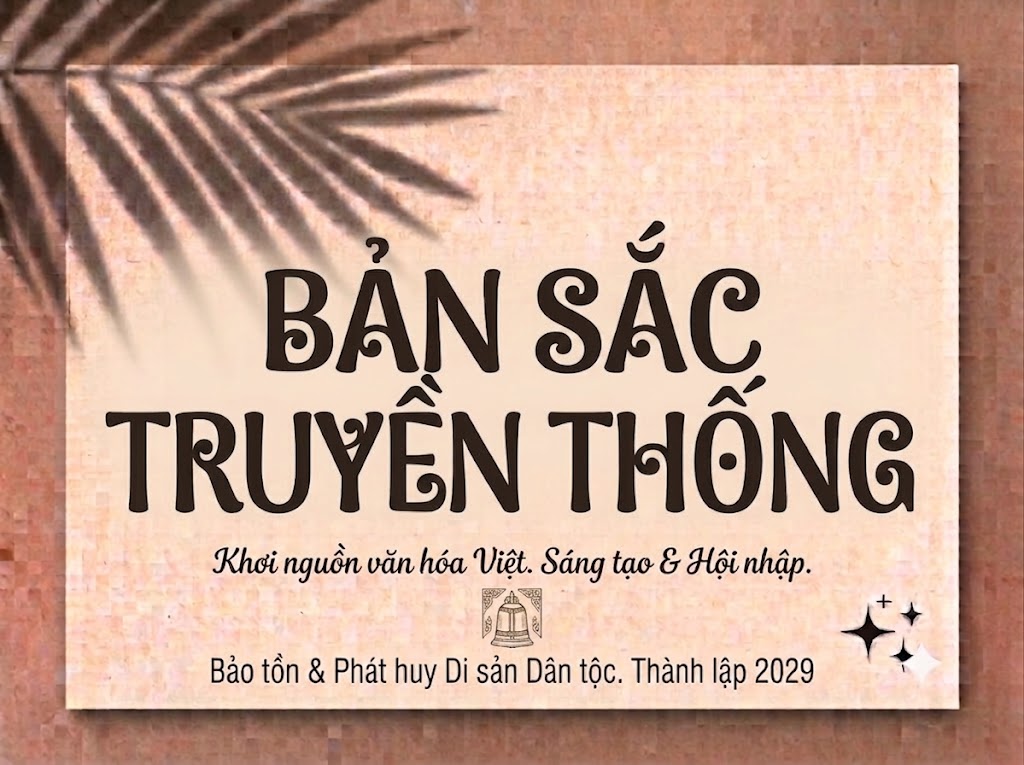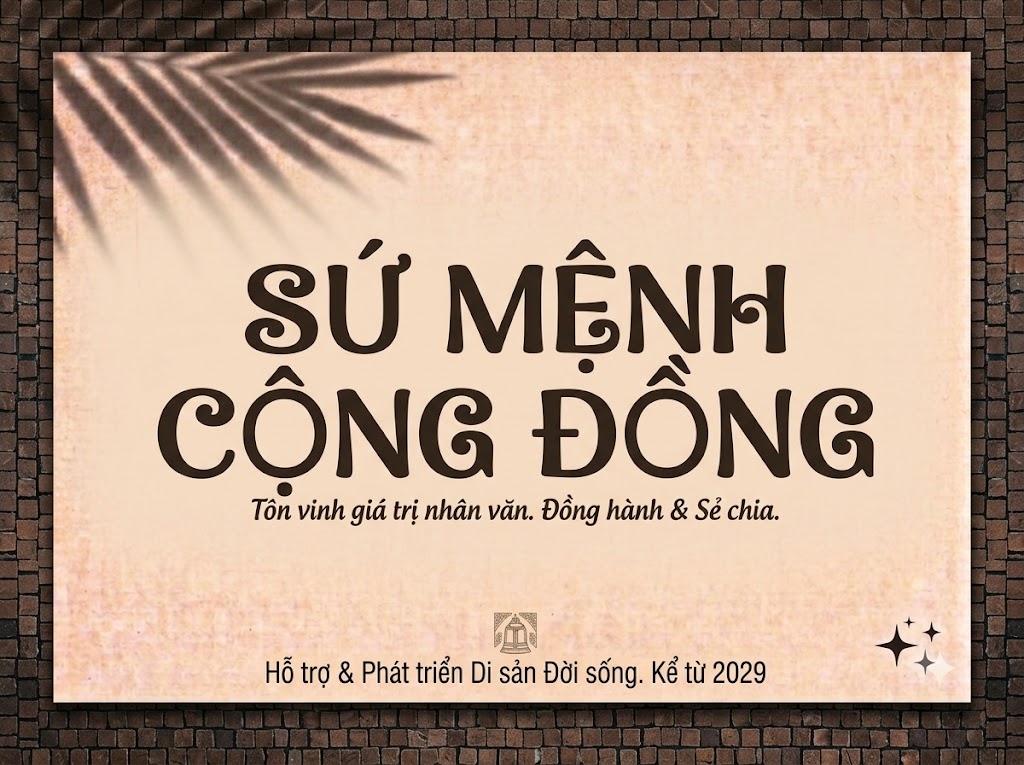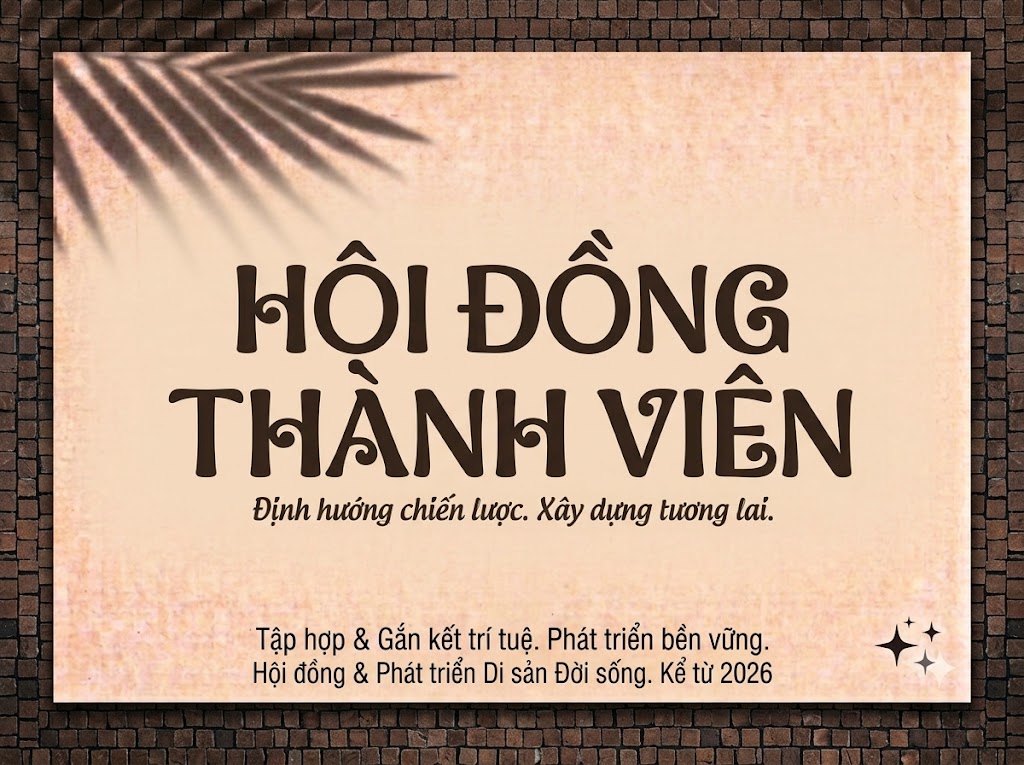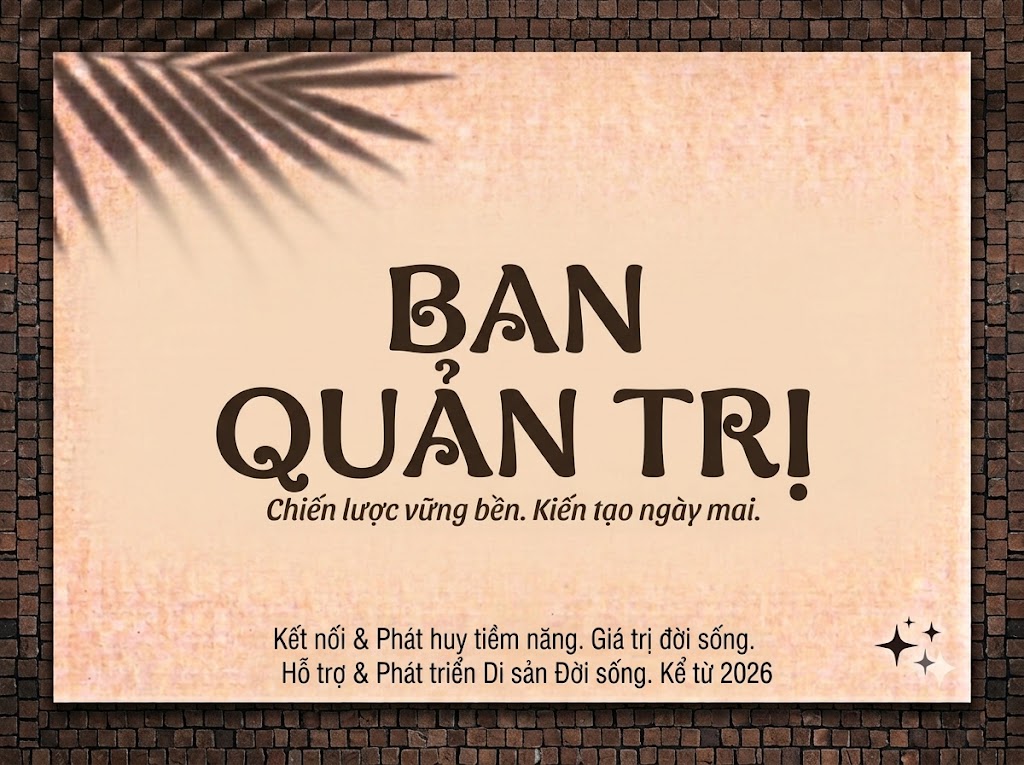
1FTV VIP Boruna
Trong xu hướng thiết kế đồ họa đương đại, ranh giới giữa chữ viết (typography) và hội họa ngày càng trở nên mờ nhạt. Một phông chữ tiêu đề xuất sắc giờ đây không chỉ làm nhiệm vụ truyền tải thông tin đơn thuần, mà bản thân nó phải là một tác phẩm nghệ thuật có khả năng tự kể câu chuyện của riêng mình.
Nếu bạn đã quá quen thuộc với các dòng Serif tân cổ điển thẳng thớm, nghiêm nghị và đang tìm kiếm một làn gió mới vừa sang trọng, quý phái lại vừa có nét uốn lượn, bay bổng đầy ma mị, thì 1FTV VIP Boruna chính là câu trả lời hoàn hảo dành cho bạn.
Giới thiệu về font 1FTV VIP Boruna
Font 1FTV VIP Boruna là một bộ chữ hiển thị có chân (serif display) mang phong cách nghệ thuật đương đại, nổi bật với sự kết hợp táo bạo giữa cấu trúc chữ Serif cao cấp và các nét cắt lượn sóng đầy mê hoặc.
Tên phông chữ: 1FTV VIP Boruna.
Đặc điểm thiết kế độc bản của VIP Boruna
Sức hút thị giác đầy mê hoặc của font 1FTV VIP Boruna đến từ sự kết hợp tài tình giữa cấu trúc hình khối hiện đại và vũ điệu “chất lỏng” mềm mại:
Độ tương phản nét cực hạn (High Contrast): Thừa hưởng DNA của dòng Modern Serif cao cấp, phông chữ sở hữu các nét dọc cực kỳ dày dặn, vững chãi đặt cạnh những nét ngang siêu mảnh. Sự tương phản này tạo nên một hiệu ứng thị giác vô cùng kịch tính và sang trọng.
Biến điệu lượn sóng (Liquid/Wave Accents): Điểm đắt giá nhất của VIP Boruna nằm ở cách tạo hình các nét cắt lượn sóng cực kỳ nghệ thuật ở phần bụng và tâm chữ cái. Nhìn vào các ký tự như o, e, a, g, p, bạn sẽ thấy các đường sóng ngang mềm mại phân tách tâm chữ một cách ngẫu hứng. Chi tiết này gợi liên tưởng đến những gợn sóng nước lăn tăn hay xu hướng thiết kế “Y2K liquid” đang rất thịnh hành.
Chân chữ vạt nhọn (Flair Serif) sắc sảo: Phần chân chữ được gọt giũa dứt khoát, gọn gàng, giúp cân bằng lại sự mềm mại của các đường lượn sóng, giữ cho kết cấu chữ luôn có sự vững chãi, uy nghiêm cần có.
Hỗ trợ hoa – thường linh hoạt: Bộ font tích hợp trọn vẹn cả hệ thống chữ viết hoa và viết thường đồng bộ. Các chữ cái viết thường vẫn giữ nguyên tinh thần lượn sóng nghệ thuật, giúp bạn dễ dàng phối hợp bố cục một cách uyển chuyển và thoáng mắt.
Hình ảnh demo thực tế của font 1FTV VIP Boruna
Kích thước nhỏ (12pt – 24pt): Dù sở hữu các nét cắt lượn sóng tinh xảo bên trong thân chữ, cấu trúc chữ đứng và bộ chữ viết thường vẫn hiển thị rất rõ ràng, ngay ngắn và dễ đọc trên màn hình điện thoại.
Kích thước lớn (36pt – 72pt): Đây chính là “đất diễn” hoàn hảo nhất của VIP Boruna. Các đường cắt rỗng lượn sóng ở chữ o, e, a hiện lên vô cùng sắc nét, cuốn hút, tạo nên một điểm nhấn typographic cực kỳ mạnh mẽ và nghệ thuật.
Ứng dụng thực tế trong thiết kế và sáng tạo nội dung
Sở hữu nét cá tính sang trọng, bay bổng và đầy chất nghệ thuật, font 1FTV VIP Boruna là vũ khí đắc lực để nâng cấp diện mạo thị giác cho các dự án:
Làm tiêu đề video ngắn (TikTok, Reels, Shorts): Đối với các video dạng cinematic, lookbook thời trang, vlog phong cách sống nghệ thuật hay review mỹ phẩm, trang sức cao cấp, cụm từ khóa chính sử dụng VIP Boruna sẽ thu hút người xem dừng lại ngay lập tức nhờ phom chữ đứng gọn gàng, hiển thị cực đẹp trên khung hình dọc 9:16.
Thiết kế ảnh thu nhỏ (Thumbnail) đầy tính thẩm mỹ: Phù hợp cho các kênh YouTube, TikTok làm nội dung về âm nhạc lofi, acoustic, chữa lành, hoặc review nghệ thuật cần một vẻ ngoài tinh tế, sang trọng để bứt phá tỷ lệ nhấp chuột (CTR).
Nhận diện thương hiệu phân khúc Luxury: Rất thích hợp làm logo dạng chữ, biểu ngữ quảng cáo, menu nhà hàng/khách sạn cao cấp, thiết kế nhãn mác, bao bì cho các sản phẩm nước hoa, spa, váy cưới hoặc local brand thời trang hướng tới sự thanh lịch, quý phái.
Ấn phẩm in ấn nghệ thuật: Hoàn hảo để làm tiêu đề bìa sách, poster triển lãm, thiệp mời sự kiện VIP hay các thiết kế artwork thời trang đầy phá cách.